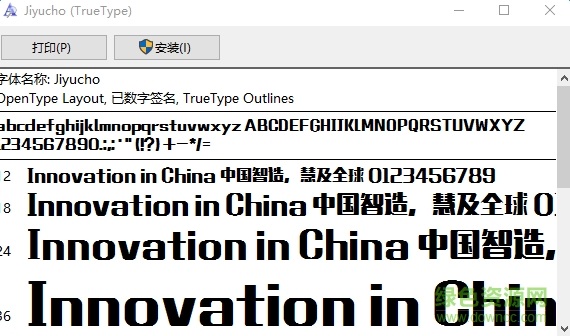
非常規(guī)黑體是一款很有特點的電腦黑體字體,就像這款字體的名字一樣它是比一般黑體字體都要粗黑的,但是這并不影響它的使用性,依舊可以用于很多地方,歡迎有需要的朋友來綠色資源網下載。
非常規(guī)黑體字體是一款很不錯的電腦字體,寫出來的字特別的粗黑,可以用于書畫題字題詞等,大家如果需要這款字體可以隨時來綠色資源網下載。